แบบอักษรสมัยใหม่กว่า 50 แบบเพื่อใช้บนเว็บไซต์ WordPress ของคุณในปี 2022
เผยแพร่แล้ว: 2020-08-28เมื่อสร้างไซต์ WordPress คุณต้องมีเครื่องมือที่เหมาะสมเพื่อสร้างผลกระทบอย่างมีประสิทธิภาพ ซึ่งรวมถึงฟอนต์สมัยใหม่มากมาย!
อย่างไรก็ตาม ธีม WordPress ของคุณอาจไม่มีแบบอักษร HTML ที่คุณต้องเลือก หรือคุณอาจไม่พอใจกับรายการที่เลือกไว้สำหรับคุณ
อะไรทำให้ฟอนต์ทันสมัยได้จริง?
แบบอักษรสมัยใหม่ไม่ใช่เรื่องใหม่เลย สไตล์นี้เดิมพัฒนาขึ้นในศตวรรษที่ 18 อย่างไรก็ตาม การออกแบบของพวกเขายังคงมีความเกี่ยวข้องในโลกสมัยใหม่ อันที่จริงคุณเห็นพวกมันทุกที่อย่างแท้จริง
แล้วฟอนต์สมัยใหม่หน้าตาเป็นอย่างไร?
แบบอักษรสมัยใหม่มีความคม เพรียวบาง ตัวหนา แบบมืออาชีพและมีสไตล์ พวกมันมักจะเป็นซานเซอริฟ (แต่ไม่เสมอไป) และบางครั้งก็เข้ากับหมวดหมู่ฟอนต์ตัวสะกดได้ การออกแบบของพวกเขามีความโดดเด่นในทันทีและมักใช้ในส่วนหัวและโลโก้ พวกเขาสามารถเป็นองค์กรที่ชัดเจน แต่ไม่ก้าวร้าว ค่อนข้างจะกล้าหาญและเรียกร้องความสนใจ
นี่คือตัวอย่างไซต์พอร์ตโฟลิโอที่ใช้ฟอนต์สมัยใหม่
สังเกตว่ามันกระชับและแคบขนาดไหน?
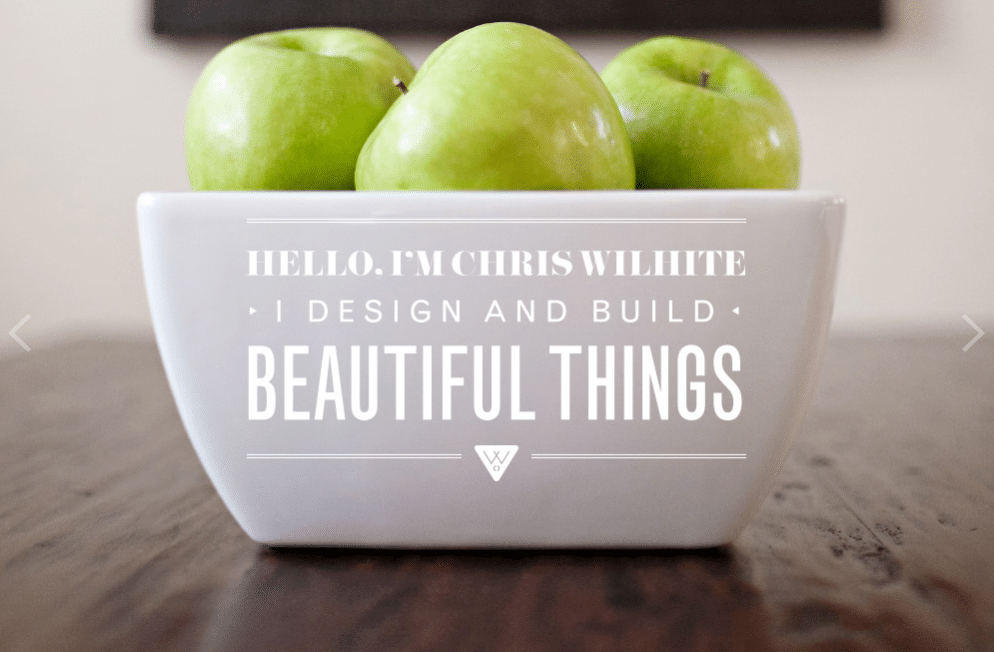
สิ่งเหล่านี้เป็นเรื่องทั่วไปแน่นอน การออกแบบตัวอักษรสมัยใหม่ได้พัฒนาขึ้นและคุณมักจะพบตัวอย่างโวหารมากขึ้นเช่นกัน แต่หวังว่านี่จะทำให้คุณได้แนวคิดทั่วไปว่าฟอนต์สมัยใหม่คืออะไร (และทำไมคุณถึงอยากใช้ฟอนต์นั้น)
56 แบบอักษรที่ทันสมัยที่สุดที่จะใช้ในปี 2022
1. บทนำ
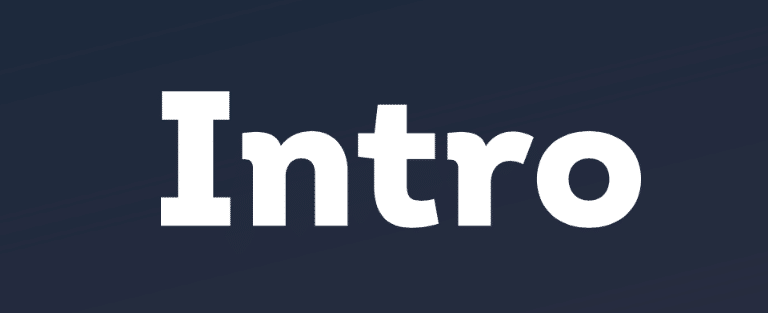
Intro เป็นฟอนต์ที่ดูทันสมัยที่มีเส้นหนาและการนำเสนอ ซึ่งสามารถใช้สำหรับส่วนหัวหรือชื่อเรื่องได้อย่างง่ายดาย ตระกูลฟอนต์นี้มี 72 ฟอนต์ที่มีน้ำหนักต่างกัน 8 แบบ ตั้งแต่แบบบางไปจนถึงแบบหนา ให้คุณมีความยืดหยุ่นสูง
2. โคโมดะ
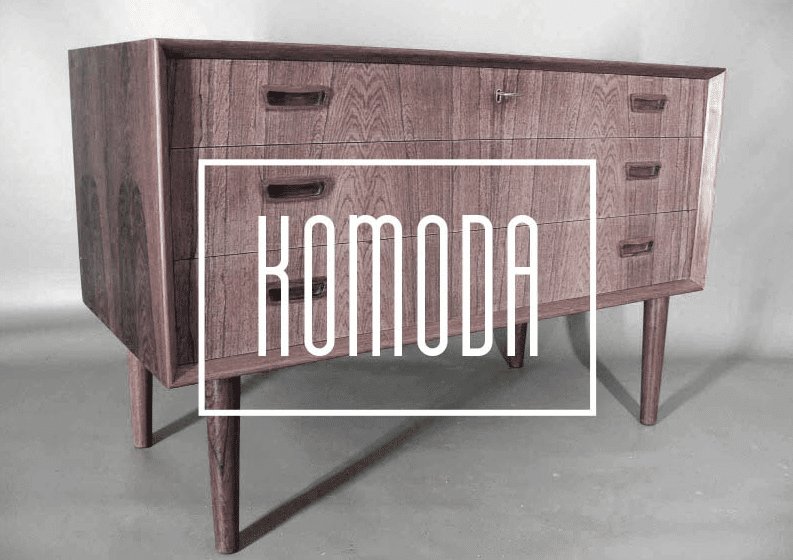
อีกทางเลือกหนึ่งคือโคโมดะ แบบอักษรนี้กระชับและน่าสนใจเป็นอย่างยิ่ง มันคือตัวพิมพ์ใหญ่และซานเซอริฟทั้งหมดที่มีรูปลักษณ์แบบบล็อกโดยที่เส้นกึ่งกลางของตัวอักษรแต่ละตัวถูกยกขึ้นสูง และการผูกมัดของมันทำให้คำแถลง ทางเลือกที่สมบูรณ์แบบสำหรับโลโก้ที่นี่
3. Stoked
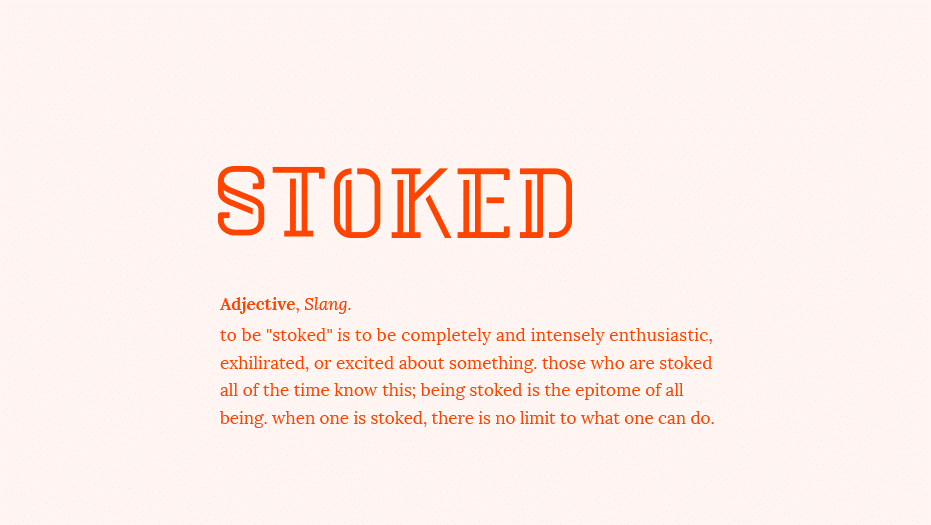
Stoked เป็นอีกตัวเลือกตัวพิมพ์ใหญ่ที่ให้รูปลักษณ์ที่เป็นเอกลักษณ์สำหรับส่วนหัวและโลโก้ เป็นเรื่องที่น่าสนใจในขณะที่ยังคงอ่านได้ คุณลักษณะที่กำหนดคือการรวมเส้นคู่บนตัวอักษรแต่ละตัว รวมถึงการขึ้นบรรทัดใหม่ที่ทำให้มีลักษณะเป็นลายฉลุ
4. มาริสา สุดเก๋
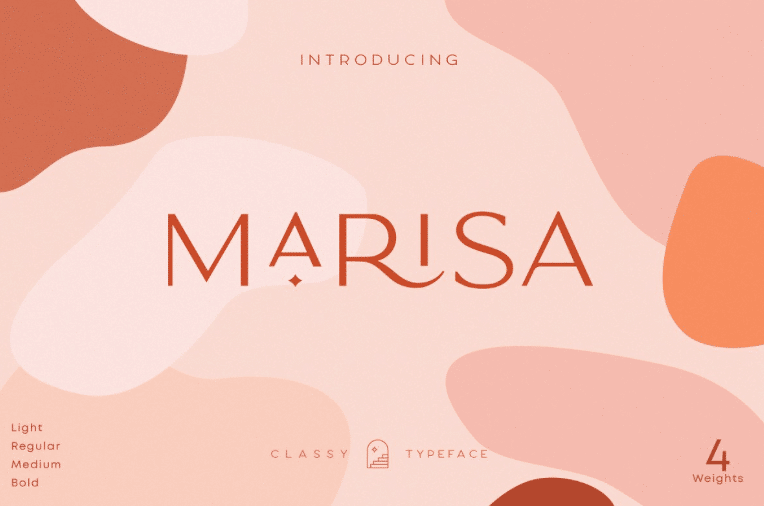
มีคลาสซี่มาริสาด้วย แบบอักษรที่ทันสมัยนี้มีความสง่างามและลื่นไหล โดยมีตัวเลือกแบบอักษรที่บางและสวยงามกว่าสำหรับโลโก้และส่วนหัวของคุณ มันมีอักษรควบ ร่ายมนตร์ทางเลือก และเครื่องประดับที่น่าสนใจจริงๆ ที่เพิ่มตัวละครเพิ่มเติมให้กับข้อความที่คุณต้องการแชร์
5. แคนเตอร์
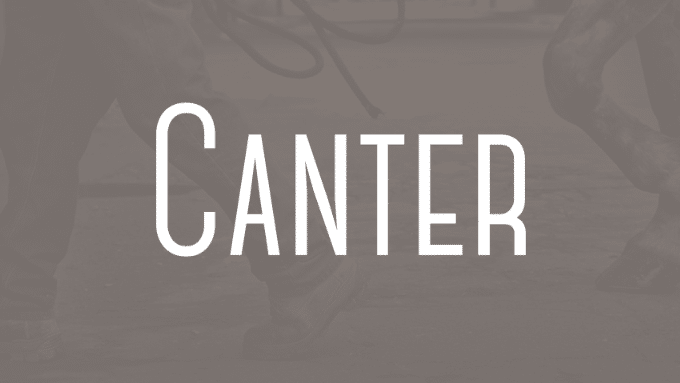
Canter เป็นอีกหนึ่งทางเลือกที่ดี อันนี้เป็นฟอนต์ sans serif ที่มีตัวพิมพ์ใหญ่ทั้งหมดและมีระยะห่างแบบย่อ มันมาในน้ำหนักที่แตกต่างกันหกแบบเช่นกัน รวมถึงตัวเลือก 3 มิติและอีกอันที่มีเงาตกกระทบที่โดดเด่น
6. โชคดี
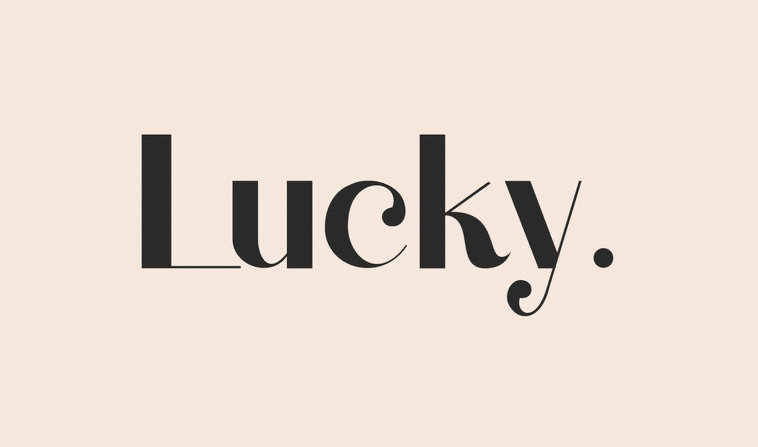
Lucky เป็นฟอนต์ที่ทันสมัยอีกตัวที่น่าพิจารณา เป็นการเลือก Sans serif อื่นที่สามารถทำงานได้ดีกับโลโก้หรือส่วนหัว มีคุณภาพด้านบรรณาธิการที่ชัดเจนและสามารถนำไปใช้กับนิตยสารและสิ่งพิมพ์ออนไลน์ได้อย่างง่ายดาย
7. ซาฟีร์
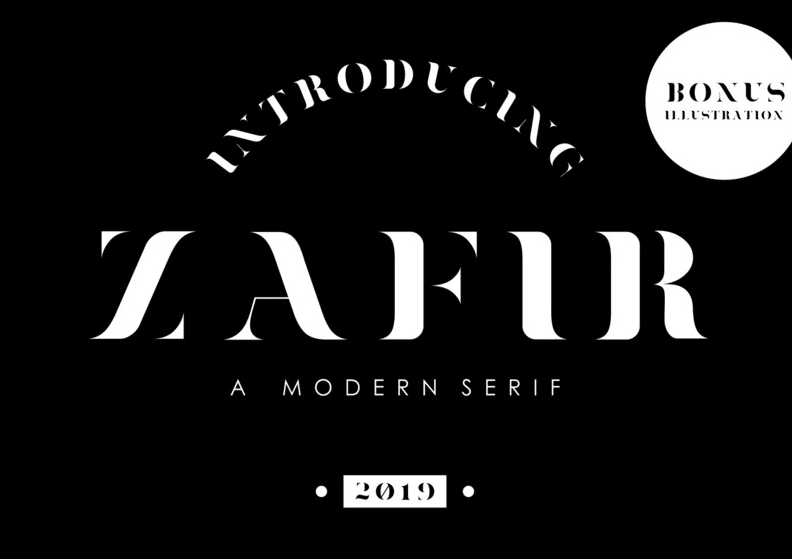
Zafir เสนอตัวเลือกแบบอักษรที่ทันสมัยอีกตัวที่ควรพิจารณา มันน้อยมากในการนำเสนอ Zafir เป็นอีกทางเลือกหนึ่ง เป็นแบบอักษร serif ที่มีเส้นโค้งและรูปลักษณ์ที่น่าสนใจโดยรวมที่สามารถทำงานได้ดีสำหรับโลโก้และชื่อ
8. โคฟส์
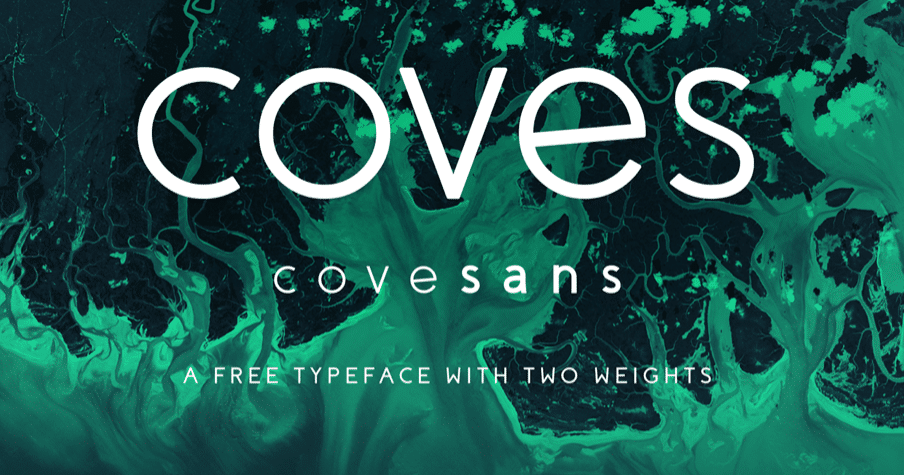
หรือคุณสามารถใช้ Coves มันมาพร้อมกับน้ำหนักสองแบบ เบาและหนา และมีตัวเลือกฟอนต์ที่หรูหราและคล่องตัวสำหรับโปรเจ็กต์ล่าสุดของคุณ ใช้สำหรับข้อความมาตรฐานและสำหรับชื่อเรื่องและส่วนหัวด้วย อเนกประสงค์จริงๆ
9. Azonix
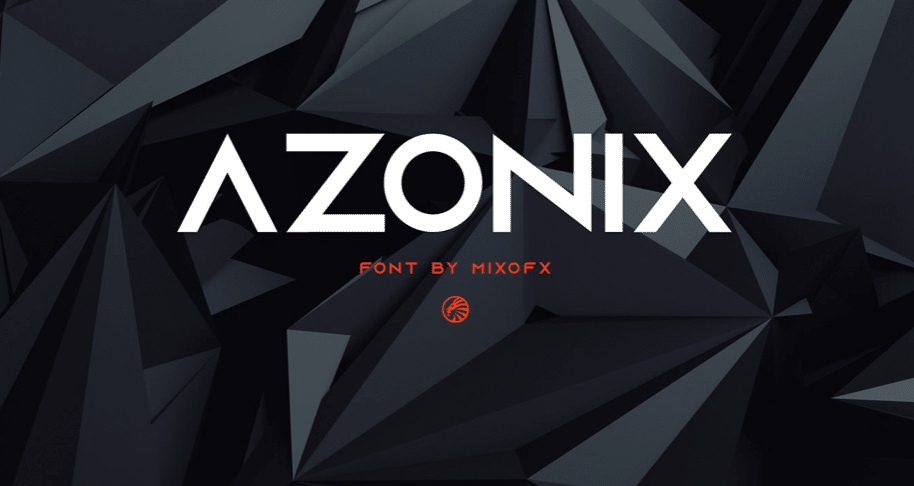
Azonix นำเสนอการเลือกแบบอักษรที่ทันสมัยอีกครั้ง คราวนี้มีการโค้งงอล้ำยุค เป็นแบบอักษรซานเซอริฟที่เน้นรูปลักษณ์ทางเรขาคณิต มันเป็นตัวพิมพ์ใหญ่ทั้งหมดและดูเหมือนว่าสามารถใช้ในลำดับเครดิตเปิดของภาพยนตร์ไซไฟได้อย่างง่ายดาย
10. อาร์คิป
Arkhip เป็นอีกหนึ่งการเลือกแบบอักษรฟรีที่รักษาการออกแบบที่ทันสมัยในขณะที่หวนนึกถึงยุคสมัยที่ล่วงไป ใช้องค์ประกอบของแบบอักษรรัสเซียเพื่อสร้างสิ่งใหม่ที่ทันสมัยอย่างแท้จริง
11. ไพรม์
มีแบบอักษรอื่นที่เรียกว่า Prime เป็นฟอนต์ซานเซอริฟสมัยใหม่ที่มีเส้นหนาและมีรูปลักษณ์ที่ล้ำสมัยโดยรวม มีมุมเรขาคณิตและดูสมบูรณ์แบบสำหรับเว็บไซต์แนวอนาคตหรือเทคโนโลยี
12. ลูกโลก
Glober เป็นฟอนต์สมัยใหม่อีกตัวที่คุณควรลองดู ตระกูลแบบอักษรนี้ประกอบด้วยน้ำหนัก 18 ตัวโดยแบ่งเป็นเสา 9 ตัวและตัวเอียง 9 ตัว เป็นฟอนต์ซานเซอริฟที่อ่านง่ายและนำไปใช้กับสถานการณ์ต่างๆ ได้ง่าย รวมทั้งชื่อและเนื้อหา
13. อ่อนโยน
MADE Gentle เป็นแบบอักษรสมัยใหม่อีกรูปแบบหนึ่งที่คู่ควรแก่การพิจารณา ถือว่าเป็นซอฟต์เซอริฟและได้รับแรงบันดาลใจจากฟอนต์ Cooper Black อันนี้เป็นตัวหนา แต่โค้งมน และดูชวนให้นึกถึงปกหนังสือและป้ายเก่าจากปี 1970
14. นอร์ดิก
นอร์ดิกมีทั้งแบบสมัยใหม่และแบบคลาสสิกมีแบบอักษรสองแบบและน้ำหนักสามแบบให้เลือก การออกแบบได้รับแรงบันดาลใจจากอักษรรูนของนอร์เวย์ และเหมาะสำหรับใช้ในชื่อเรื่อง หัวเรื่อง และโลโก้
15. Maddac
แบบอักษร Maddac นำเสนอตัวเลือกที่มีสไตล์สำหรับเว็บไซต์ของคุณ เป็นตัวหนา บล็อก และซานเซอริฟ มีการออกแบบที่ทันสมัยและมีเอกลักษณ์ในการใช้งาน ตัวอักษรแต่ละตัวมีมุมเล็กน้อยหรือเอียงไปทางใดด้านหนึ่งของการออกแบบ ซึ่งให้สไตล์เล็กน้อยแก่สมการ
16. จระเข้
Croc เป็นฟอนต์ที่ยอดเยี่ยมไม่ใช่หรือ? มันเป็นแบบอักษรเซอริฟตัวหนาที่มีสไตล์อันเป็นเอกลักษณ์ที่ชวนให้นึกถึงอดีตในขณะที่ยังคงความสด
17. อควา
Aqua เป็นแบบอักษรอื่นที่คุณควรพิจารณา อันนี้มีคุณสมบัติแบบอาร์ตนูโวที่ทำให้ดูไร้กาลเวลา เป็นตัวหนาแต่เรียบง่ายและมีการตกแต่งและสายรัดที่ทำให้โดดเด่นจากแบบอักษรอื่นๆ ที่คล้ายคลึงกัน
18. ประกาศ
แสดงความเป็นตัวหนาด้วย Manifesto แบบอักษรนี้ได้รับแรงบันดาลใจจากขบวนการเหตุผลนิยมของอิตาลีและมีคุณสมบัติด้านบรรณาธิการอย่างแน่นอน ใช้สำหรับหัวเรื่อง โลโก้ และชื่อเรื่อง ใช้สำหรับการพิมพ์และการออกแบบออนไลน์ มันใช้งานได้หลากหลายอย่างแท้จริง
19. ออร์กนีย์
Orkney เป็นแบบอักษรที่ดูเป็นมืออาชีพที่น่ารัก แบบอักษรเป็นแบบเรขาคณิตในการออกแบบและสามารถใช้งานได้หลากหลายวัตถุประสงค์ ใช้สำหรับชื่อหรือโลโก้ ใช้สำหรับข้อความมาตรฐาน ใช้ในสื่อสิ่งพิมพ์หรือสื่อดิจิทัล ท้องฟ้าเป็นขีด จำกัด ที่นี่
20. เอลปปา
Elppa มีลุคล้ำยุคที่น่าดึงดูดใจและมีหลายแง่มุม แบบอักษรนั้นค่อนข้างเล็กในขณะที่ยังจับความรู้สึกแบบยุคอวกาศ ใช้สำหรับการพิมพ์และการออกแบบเว็บ มันจะใช้ได้กับโลโก้และชื่อ อาจไม่ใช่ข้อความเนื้อหา แต่มีประโยชน์อย่างแน่นอนสำหรับกราฟิกและอื่นๆ
21. ข้าวโพด
ข้าวโพดเป็นแบบอักษรที่น่าสนใจที่มีมุมมนและให้ความรู้สึกแบบฟาร์ม ประกอบด้วยสไตล์ที่แตกต่างกัน 14 รูปแบบ ซึ่งคุณสามารถเริ่มใช้งานได้ทันทีสำหรับชื่อเรื่อง ส่วนหัว และโลโก้ บางสไตล์สามารถใช้กับข้อความเนื้อหาได้หากต้องการ คุณสามารถสร้างการออกแบบเว็บไซต์ทั้งหมดได้ด้วยสิ่งนี้
22. โคลิโกะ
หรือคุณอาจเลือกใช้ Koliko แบบอักษรแสนสนุกที่ดึงดูดใจในทันทีเพื่อวัตถุประสงค์ที่หลากหลาย มาพร้อมกับสามสไตล์ แต่ละแบบโอบรับการแต่งงานที่สมบูรณ์แบบของรูปแบบและการทำงาน
23. เล่นโวหาร
Quirk เป็นฟอนต์ที่ดูแปลกตาทีเดียว ชื่อของมันเป็นทางเลือกที่ดี เป็นฟอนต์ตัวพิมพ์ใหญ่ที่มีตัวอักษรควบและองค์ประกอบที่วางซ้อนกันได้
24. เลอฝรั่งเศส
Le French เป็นตัวเลือกแบบอักษรที่ซับซ้อน โดยเฉพาะอย่างยิ่งหากคุณต้องการเลียนแบบความรู้สึกคาเฟ่สไตล์ฝรั่งเศสโบราณ ทางเลือกที่ยอดเยี่ยมสำหรับเมนูและเว็บไซต์เกี่ยวกับอาหารทั่วๆ ไป ใช้สำหรับหัวเรื่อง ส่วนหัว โลโก้ และเนื้อหาด้วย
25. มิวนิค
มิวนิกเป็นตัวเลือกฟอนต์ซานเซอริฟที่น่ารักซึ่งเป็นตัวเลือกที่ยอดเยี่ยมสำหรับโลโก้หรือกราฟิกชื่อ มันยืนสูงและสง่างามโดยไม่คุกคาม
26. ภาคตะวันตกเฉียงเหนือ
Northwest เป็นฟอนต์สไตล์โมเดิร์นที่ให้ความรู้สึกย้อนยุค มันชวนให้นึกถึงโลโก้เฟืองของแคมเปญและชื่อนิตยสารกลางแจ้ง ด้วยเซอริฟแบบกล่องและองค์ประกอบตกแต่ง ฟอนต์นี้จะทำงานได้ดีสำหรับเนื้อหาที่มีธีมกลางแจ้งทุกประเภท
27. โมเดก้า
โมเดก้านั้นดูโฉบเฉี่ยวและทันสมัยและตรงไปตรงมาสุดๆ เป็นทางเลือกที่ทันสมัยที่สามารถปรับใช้งานได้หลากหลายรูปแบบ ด้วยการเพิ่มมุมบนตัวอักษรแต่ละตัว มันนำเสนอสไตล์ที่เป็นเอกลักษณ์ที่อาจเหมาะกับโครงการต่อไปของคุณ
28. ข้อจำกัดความรับผิดชอบ
ข้อจำกัดความรับผิดชอบคือตัวเลือกแบบอักษรที่แคบและหนาซึ่งเหมาะสำหรับวัตถุประสงค์ที่หลากหลาย มีสไตล์ที่อัดแน่นเป็นพิเศษที่ทำให้ตัวอักษรดูโดดเด่นและสง่างาม นี้จะทำงานได้ดีสำหรับส่วนหัวหรือชื่อ
29. 5th อเวนิว
5th Avenue เป็นร้านแนวแฟนซีที่มีอากาศคลาสสิกที่เหมาะกับโลโก้และตราสินค้าอย่างเป็นทางการ เป็นแบบอักษรตัวหนาพร้อมเซอริฟที่โดดเด่นเนื่องจากมีตัวอักษรทางเลือกมากมายที่เพิ่มสไตล์และความน่าสนใจ
30. ควาเกียซ
Quakiez เป็นอีกหนึ่งตัวเลือกแบบอักษรที่ทันสมัยซึ่งมีตัวเลือก serif ให้กับรายการของเรา ได้รับการออกแบบโดยคำนึงถึงความหรูหรา แต่ยังคงองค์ประกอบของความเรียบง่าย มาพร้อมสองสไตล์และใช้สำหรับโลโก้ ชื่อเรื่อง ส่วนหัว และอื่นๆ
31. กลางแจ้งที่ทันสมัย
หรือคุณสามารถเลือกใช้ Modern Outdoor และเรียกใช้การตั้งแคมป์และกิจกรรมกลางแจ้งได้ทันที แบบอักษรนี้เหมาะสำหรับชื่อ ส่วนหัว และโลโก้ และจะสร้างผลกระทบอย่างแท้จริงต่อโปสเตอร์ มันเรียกร้องความสนใจและใส่หมวกสวยทุกใบเพื่อให้รู้สึกกลางแจ้ง
32. ไฮเพอร์โบลา
ไฮเปอร์โบลานั้นโค้งมนและเป็นอนาคต อันที่จริงแล้ว มันดูกว้างใหญ่ในทางที่ดี แบบอักษรนี้มีตัวนับโค้งมนในขณะที่ยังคงรูปทรงกล่องโดยรวม
33. ชกมวย
แบบอักษร Boxing เป็นกล่องที่ดูสะอาดตา เหมาะสำหรับส่วนหัว ชื่อเรื่อง และโลโก้ ตัวพิมพ์ใหญ่ทั้งหมดสูงและน่าสนใจ เหนือสิ่งอื่นใด มันใช้งานได้ดีมากและสามารถนำไปใช้ใหม่ได้หลายวิธี
34. ซอนเดอร์
Sonder เป็นฟอนต์ที่มีหลายแง่มุมอย่างแท้จริง มันมาพร้อมกับตัวเลือกฟอนต์ slab และ sans serif มาพร้อมตุ้มน้ำหนักหลายแบบและแบบธรรมดาและแบบหยาบ สไตล์หยาบมีช่องว่างบางส่วนในตัวอักษร ทำให้ดูเรียบง่ายและเป็นธรรมชาติ
35. ลอมบอก
ลอมบอกเป็นแบบอักษรบาง ๆ ที่ดูสง่างามอย่างยิ่ง มันเป็นตัวเลือกซานเซอริฟที่มีองค์ประกอบทางเรขาคณิตที่ทำให้ดูโดดเด่นและไม่เหมือนใคร เป็นตัวเลือกที่เหมาะสำหรับส่วนหัว โลโก้ และชื่อ
36. Distrito
Distrito เป็นแบบอักษรตัวพิมพ์ใหญ่ทั้งหมดที่มีสไตล์เฉพาะตัว ตัวอักษรแต่ละตัวเอียงเล็กน้อย ให้รูปลักษณ์ที่เป็นเอกลักษณ์ซึ่งสามารถแปลได้ดีเพื่อใช้ในโลโก้และส่วนหัว นอกจากนี้ยังเป็นแบบอักษรตัวพิมพ์ใหญ่ทั้งหมดที่ได้รับแรงบันดาลใจจากการออกแบบโมดูลาร์ของ Columbian
เบื่อกับโฮสต์ที่ช้า? Kinsta สร้างขึ้นโดยคำนึงถึงความเร็วและประสิทธิภาพ ตรวจสอบแผนของเรา
37. Ailerons
Ailerons ดูเหมือนแบบอักษรที่จะปรากฏบนป้ายมนุษย์ต่างดาว และบรรลุถึงความสวยงามนี้ได้เป็นอย่างดี เป็น Sans serif และตัวพิมพ์ใหญ่ทั้งหมดและทำให้เกิดผลกระทบไม่ว่าคุณจะวางไว้ที่ใด แม้ว่าชื่อและส่วนหัวจะดีที่สุดสำหรับมัน
38. เอธนา
Ethna มีรูปลักษณ์คลาสสิก แต่มีสไตล์ที่ทันสมัย เป็นฟอนต์ตระกูล sans serif ที่ได้รับแรงบันดาลใจจากการออกแบบแนวมนุษยนิยม และทำงานได้ดีในการผสมผสานองค์ประกอบการออกแบบสไตล์วินเทจและสมัยใหม่เข้าด้วยกันเพื่อสร้างสิ่งใหม่ อันนี้ทำงานได้ดีในทุกกรณีการใช้งาน
39. โนเอล
Noelle เป็นฟอนต์ serif เรขาคณิตที่พร้อมจะสร้างความประทับใจแรกพบที่ดี มันเรียบง่ายในการออกแบบและจะทำงานได้ดีสำหรับชื่อและส่วนหัวในทุกอุตสาหกรรม มีองค์ประกอบแบบวินเทจเล็กน้อย แต่ก็ยังดูสด ใช้ออนไลน์หรือในการพิมพ์ นอกจากนี้ยังมาพร้อมกับฟอนต์สคริปต์เป็นโบนัส
40. ภาคต่อ
ผลสืบเนื่องเป็นแบบอักษรโค้งมนที่สมบูรณ์แบบสำหรับโลโก้และส่วนหัว เหนือสิ่งอื่นใด มันมาพร้อมกับสายรัดจำนวนมากที่ให้สไตล์และเพิ่มความน่าสนใจให้กับทุกสิ่งที่คุณสร้างด้วยมัน การออกแบบที่นี่มีความโดดเด่นแต่ไม่โอ่อ่า
41. สูงกว่า
Higher คือตัวเลือกแบบอักษรที่ซับซ้อนซึ่งให้รูปลักษณ์ที่คลาสสิก แบบอักษรตัวพิมพ์ใหญ่ทั้งหมดนี้มีความเข้มข้นสูงและมีความต้องการสูง นำเสนอสไตล์ทันทีสำหรับสิ่งที่คุณใช้
42. นาโน
นาโนเป็นฟอนต์ที่ไม่ใช่เซอริฟซึ่งมีรูปลักษณ์ล้ำยุคและเป็นตัวพิมพ์เล็กทั้งหมด ทำให้เป็นตัวเลือกที่ไม่เหมือนใครในรายการนี้ ตัวหนังสือเองก็มีความทันสมัยและสามารถระบุตัวตนได้ ทำให้เป็นตัวเลือกที่ยอดเยี่ยมสำหรับโลโก้และวัสดุที่มีตราสินค้าอื่นๆ ควรใช้วลีสั้นๆ แต่เนื่องจากประโยคที่ยาวกว่านั้นอาจอ่านไม่ออกเล็กน้อย
43. จอลลิน
Jollin เป็นฟอนต์สมัยใหม่ที่มีรอยหยักบนตัวอักษรบางตัวและมีลักษณะอ้วนท้วนทุกส่วน แบบอักษรซานเซอริฟนี้มาในเวอร์ชันปกติและตัวเอียง และประกอบด้วยตัวอักษรทางเลือกที่หลากหลาย เพื่อให้คุณสามารถทำให้ข้อความของคุณดูเรียบง่ายขึ้นหรือขี้เล่นขึ้นอยู่กับอารมณ์ของคุณ
44. ปรากฏการณ์
ปรากฏการณ์เป็นแบบอักษรแคบและบล็อกที่มีขอบมน มันสร้างคำชี้แจงและสามารถใช้สำหรับชื่อ โลโก้ หรือส่วนหัวได้อย่างง่ายดาย มาพร้อมสไตล์ที่แตกต่างกันถึง 7 แบบ ตั้งแต่แบบบางไปจนถึงแบบหนา ซึ่งให้โอกาสในการใช้ข้อความมาตรฐานมากมายเช่นกัน
45. ความสามารถ
Calibre เป็นฟอนต์ที่มีขนาดย่อมากซึ่งสามารถตั้งให้สูงกว่าเนื้อหาของคุณหากคุณปล่อยให้มันเป็นไปในทางที่ดี เป็นตัวเลือกตัวพิมพ์ใหญ่ทั้งหมดที่มีตัวเลข ร่ายมนตร์ และอักขระตะวันตกเพื่อการวัดที่ดี
46. วันอาทิตย์
Sundays เป็นฟอนต์ serif ที่เป็นยุคปัจจุบันอย่างแน่นอน แต่ยังให้ความรู้สึกคลาสสิกที่ปฏิเสธไม่ได้ แบบอักษรนี้บางและโค้งกว่าแบบอักษรคลาสสิกที่คล้ายกัน และมีสไตล์ที่เข้ากับส่วนหัวและชื่อนิตยสาร โลโก้เว็บไซต์ ส่วนหัว และอื่นๆ ได้
47. ศิลามุมเอก
Cornerstone เป็นฟอนต์บล็อกอีกตัวที่มีการออกแบบโมดูลาร์ที่สามารถทำงานได้ในแอพพลิเคชั่นต่างๆ ตั้งแต่โลโก้ไปจนถึงส่วนหัว
48. วันหนึ่ง
One Day เป็นฟอนต์บางๆ ที่มีเส้นแบ่งที่น่าสนใจซึ่งทำให้เป็นเอกลักษณ์ เป็นฟอนต์ตัวพิมพ์ใหญ่ทั้งหมดที่มีสไตล์บางและเบา ประกอบด้วยตัวเลขและร่ายมนตร์และให้ความรู้สึกเป็นเรขาคณิตโดยไม่ดูเป็นกล่องเกินไป
49. Kollektif
Kollektif เป็นแบบอักษรสมัยใหม่คลาสสิกที่สามารถใช้ได้หลายวิธี มีการออกแบบทางเรขาคณิตและมีตุ้มน้ำหนักสองแบบ นอกจากนี้ยังปรับให้เหมาะสมสำหรับทั้งการพิมพ์และการใช้งานเว็บ
50. ความคิดถึง
จากนั้นก็มี Nostalgia ซึ่งเป็นฟอนต์สมัยใหม่ที่มีเสน่ห์แบบย้อนยุคมากพอที่จะให้ความรู้สึกราวกับว่ามันถูกสร้างขึ้นเมื่อหลายสิบปีก่อน ประกอบด้วยแบบอักษร 3 แบบ ตลอดจนร่ายมนตร์ทางเลือก อักษรควบ และดอกไม้ มันจะเป็นทางเลือกที่ดีสำหรับโลโก้ ชื่อ โปสเตอร์ หรือบัตรเชิญ
51. เอลิเซีย
Elixia มีรูปลักษณ์ที่ไร้ตัวตนซึ่งเหมาะกับถ้ำของนักเล่นแร่แปรธาตุ เป็นรูปทรงเรขาคณิตและมีมุมของเส้นพิเศษบนตัวอักษรแต่ละตัวที่มีสไตล์ที่เป็นเอกลักษณ์
52. แซลมอน
หรือจะเลือกแซลมอนก็ได้ ฟอนต์ซานเซอริฟตัวนี้เป็นตัวหนาและมินิมอล เหมาะอย่างยิ่งสำหรับชื่อ โลโก้ และส่วนหัว เป็นการออกแบบตัวพิมพ์ใหญ่ทั้งหมดและรวมถึงเวอร์ชันเต็มและโครงร่างที่เข้าคู่กันได้ดีเช่นกัน
53. ทินนู
Thinoo เป็นฟอนต์ซานเซอริฟอีกตัวหนึ่ง มาพร้อมสไตล์บางเฉียบและมีสไตล์ตัวอักษรทั้งหมด รวมถึงตัวเลข สัญลักษณ์ และเครื่องหมายวรรคตอน เป็นมืออาชีพและสะอาด เรียบง่ายแต่สะดุดตา สิ่งนี้จะทำงานได้ดีสำหรับเว็บไซต์ทุกประเภทรวมถึงสื่อสิ่งพิมพ์
54. รักในฤดูร้อน
หรือคุณสามารถใช้ Summer Loving ฟอนต์สมัยใหม่แสนสนุกที่มีฟอนต์หลากหลายสไตล์ คุณจึงสร้างงานออกแบบทั้งหมดได้โดยใช้ฟอนต์เพียงฟอนต์เดียว มันมาพร้อมกับฟอนต์ sans และรายละเอียดของพู่กันที่สามารถเพิ่มมิติให้กับโครงการของคุณได้ทันที รวมถึงตัวควบและตัวอักษรทางเลือกด้วย
55. เงินปลอม
Silverfake เสนอตัวเลือกฟอนต์ serif ที่มีระยะห่างกันอย่างกว้างขวางสำหรับชื่อ โลโก้ ส่วนหัว และสื่อสิ่งพิมพ์ ตัวอย่างนี้จะดูดีเป็นโลโก้เสื้อยืด
56. เวียนนา
สุดท้ายมีเวียนนา แบบอักษรสมัยใหม่นี้เป็นตัวเลือก serif ที่ดึงดูดทุกสายตาของแบบอักษรคลาสสิกที่ใช้บนหน้าปกนิตยสารด้วยการดัดแปลงที่เพียงพอเพื่อดึงดูดความงามในยุคปัจจุบัน เป็นจำนวนน้อยที่สุดและมีตัวอักษรพิมพ์ใหญ่ ตัวเลข และเครื่องหมายวรรคตอนทั้งหมด
สรุป
มีสาเหตุหลายประการที่คุณอาจต้องการใช้แบบอักษรที่กำหนดเองบนไซต์ WordPress ของคุณ ไม่ว่าคุณจะต้องการให้เหมาะกับแบรนด์ของคุณมากขึ้นหรือทำให้เนื้อหาของคุณอ่านง่ายยิ่งขึ้นในทุกเบราว์เซอร์ การอัปโหลดแบบอักษรสไตล์โมเดิร์นของคุณเองก็คุ้มค่าที่จะทำ
ถึงกระนั้น กระบวนการนี้อาจดูน่ากลัวในตอนแรก คุณต้องค้นหาแบบอักษร ดาวน์โหลด วางไว้ในไฟล์ .zip จากนั้นอัปโหลดไปยังไดเร็กทอรีที่ถูกต้องบนเว็บไซต์ของคุณโดยใช้ไคลเอนต์ FTP คุณจะต้องวางข้อมูลโค้ดลงในพื้นที่ที่เหมาะสมของไฟล์ CSS ของธีมของคุณ คุณสามารถเลือกที่จะดำเนินการด้วยตนเองหรือผ่านการใช้ปลั๊กอิน (หรือคุณอาจจ้างนักพัฒนาซอฟต์แวร์ก็ได้)
ไม่ว่าคุณจะเข้าสู่กระบวนการนี้ด้วยวิธีใด คุณวางใจได้ว่าผลลัพธ์ที่ได้จะดูมีสไตล์และเพิ่มลักษณะเฉพาะให้กับรูปลักษณ์โดยรวมของเว็บไซต์ของคุณ หวังว่าคอลเลกชันของฟอนต์สมัยใหม่ที่เรารวบรวมไว้ที่นี่จะช่วยคุณในการค้นหาฟอนต์ที่เหมาะสมสำหรับไซต์ WordPress ของคุณ ไม่ว่าจะเป็นตัวหนาหรือบาง โค้งมนหรือแข็ง ประดับหรือเรียบ แบบอักษรที่คุณเลือกจะสร้างความประทับใจได้!